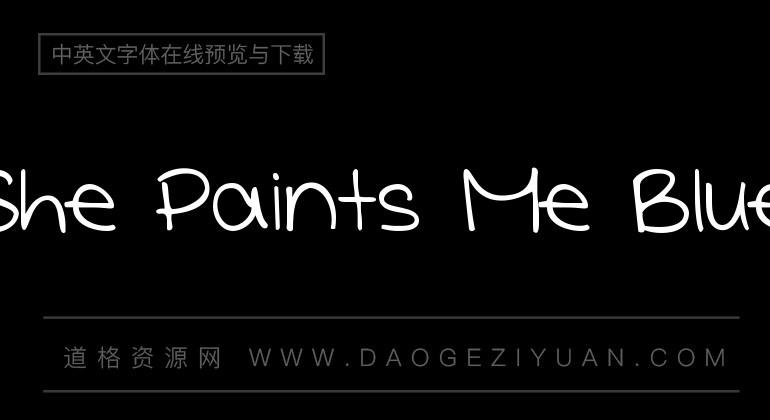
She Paints Me Blue 是一款美丽的手写字体,由英国设计师Charlotte Ager设计。它具有细腻的质感,充满活力,可以用于拼写单词、绘制优雅的线条和装饰图案。它可以用于各种类型的设计,可以添加一丝温暖的色彩,给人以柔和的感觉,是一款很棒的设计字体。内容介绍
She Paints Me Blue是一款非常不错的手写艺术字体,具有很好的视觉感,适合于文化类的宣传设计、商业类品牌的广告和产品包装设计以及个性化文字排版等较多场景。